Points forts de la fonderie Device
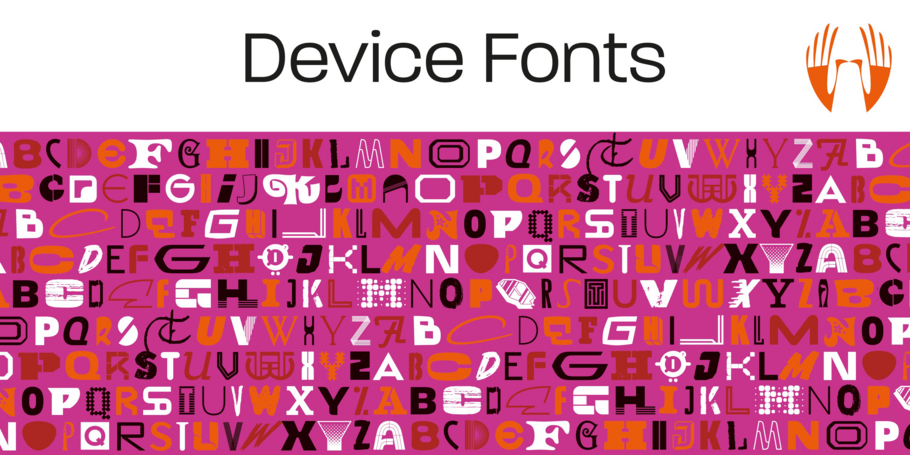
Device.
Device Fonts est la division spécialisée dans les polices de caractères du studio Device de Rian Hughes. Située à Kew Gardens, à l’ouest de Londres, elle a vu le jour en 1997 pour publier la bibliothèque de polices sans cesse plus étendue de Rian Hughes. La fonderie a créé plus de 200 polices originales couvrant plus de 1 000 graisses différentes, notamment des designs personnalisés pour des clients aussi diversifiés que les magazines Mac User (informatique) et 2000 AD (BD de science-fiction) ou Les Tortues Ninja. Hughes s’appuie sur sa carrière de dessinateur de BD et sur son métier de designer, illustrateur et lettreur pour créer une large palette de styles de polices.
Register
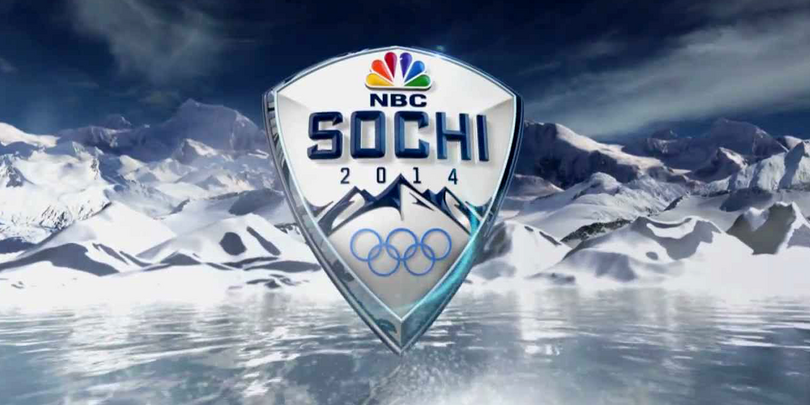
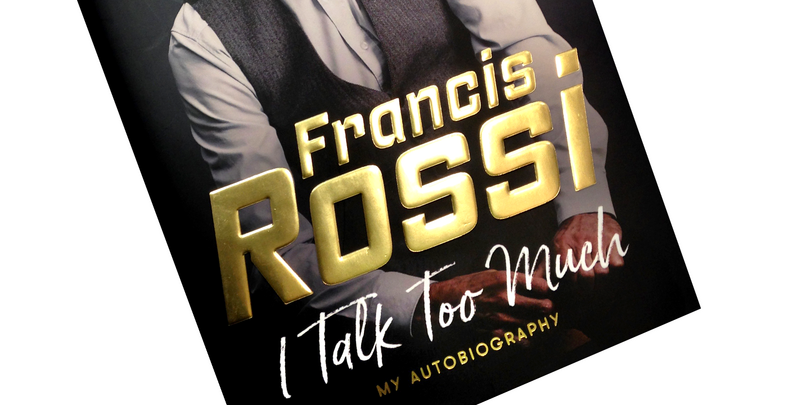
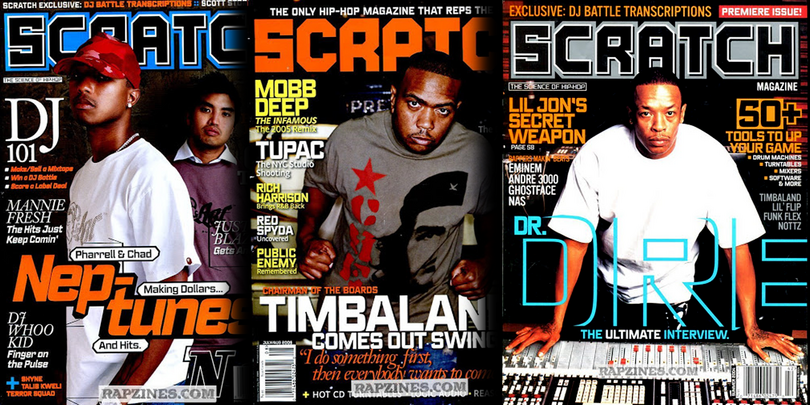
Les capitales de la police Register sont construites sur le même modèle que celles de la police Bank Gothic 1930 créée par Morris Fuller Benton pour American Type Founders, mais les courbes larges sont ici aplanies et des pièges à encre sont ajoutés pour souligner l’esthétique industrielle. Register offre également des caractères minuscules qui font défaut dans la police Bank Gothic. Ce type est disponible en deux largeurs principales, toutes deux déclinées en cinq graisses, y compris pour les graisses italiques aux formes dérivées des lettres cursives, auxquelles s’ajoute une version grasse condensée. Register a été utilisé aux Jeux olympiques de Sochi, dans le magazine Source et sur les albums publiés par Transient Records.
Regulator Nova
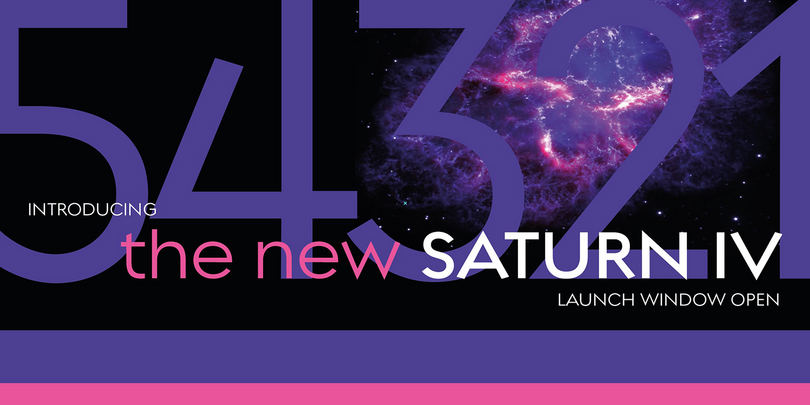
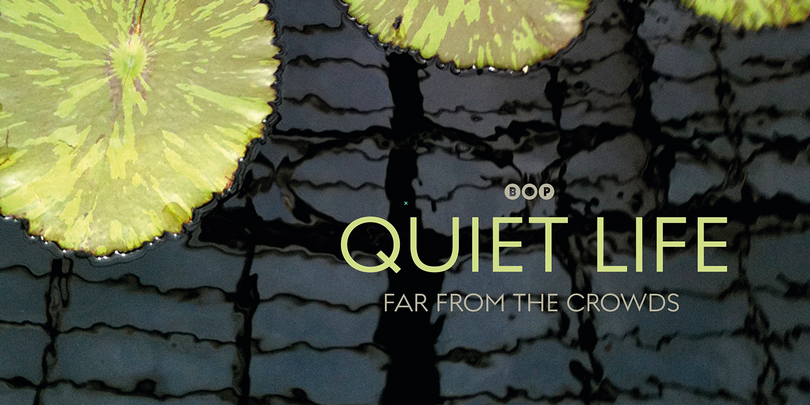
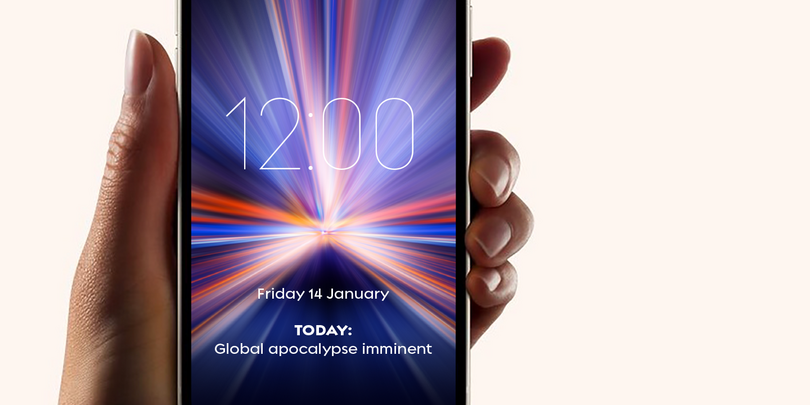
Type géométrique sans empattement se démarquant par la grande hauteur d’x des minuscules et des contreformes ouvertes, Regulator Nova est extrêmement lisible pour les corps de texte et les paramètres étendus, mais la gamme de graisses permet également de l’utiliser pour les titres. Les terminaisons des fûts présentent toutes des coupes à près de 90 degrés, ce qui confère une grande précision aux caractères. Des versions alternatives des glyphes g, j, r, w, K, R, W, # et de l’esperluette sont disponibles en graphie standard et italique, et il est possible de basculer de l’une à l’autre dans le panneau Opentype ou dans la palette de glyphes. Nette, élégante et lisible, Regulator Nova est une police aux proportions classiques basée sur un cercle et un carré circonscrits. Elle présente des similitudes structurelles avec les premiers types sans empattement comme Kabel de Rudolf Koch, mais adopte des formes plus britanniques pour les lettres « M » et « R ».
English Grotesque
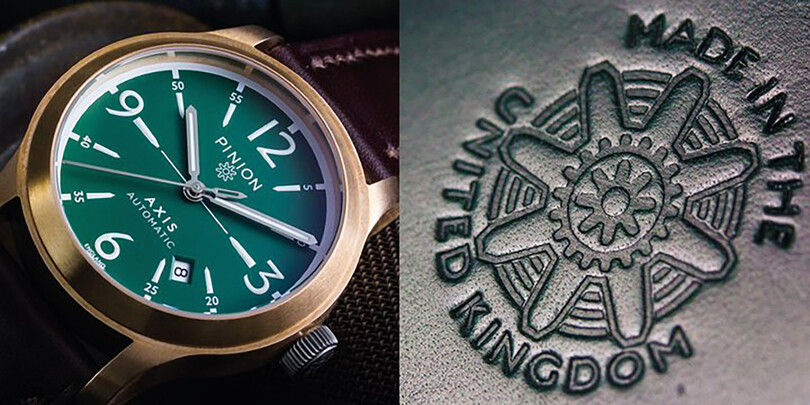
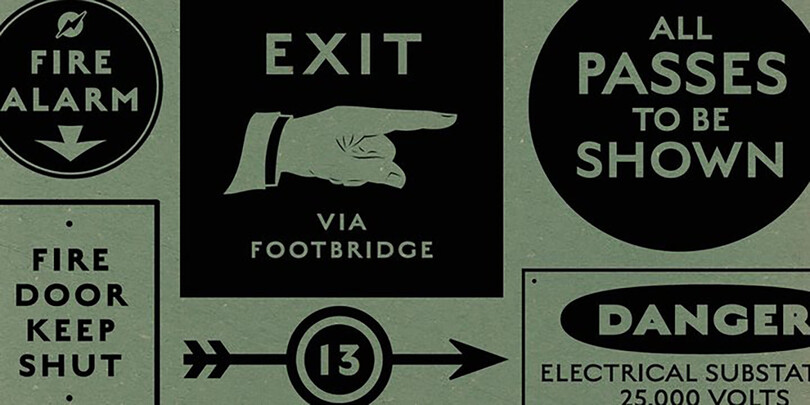
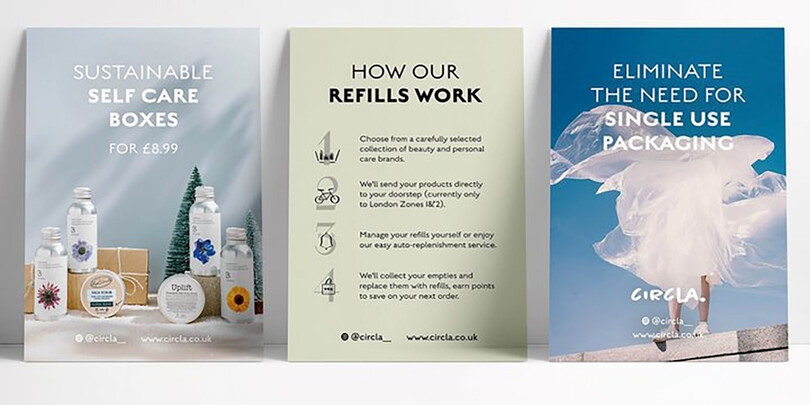
English Grotesque est un type basé sur les proportions d’un sans serif conçu au début du XXe siècle, mettant en exergue les singularités des polices de cette période. Partageant la même construction ronde et carrée des types romains Gill Sans ou Johnston Railway, ce type se caractérise par un « T » et un « W » larges, un « S » étroit et un « R » à long jambage. Du fait que l’alphabet romain ne comprenait pas de minuscules, les premiers types sans empattement empruntaient le modèle des lettres manuscrites ou cursives pour former leurs minuscules, ce qui transparaît dans la largeur plus uniforme des caractères. Par contraste, English Grotesque reprend les proportions plus distinctives des majuscules dans les minuscules. Disponible en six graisses, avec des versions alternatives en option pour les glyphes Q, &, £ et J.
Ministry
Ministry est basé sur l’alphabet utilisé à l’origine par le ministère britannique des Transports, soit un type comprenant uniquement des capitales et une seule graisse. Initialement créé dans les années 1930 pour la signalétique du réseau routier britannique, il a ensuite évolué sous l’impulsion de divers designers. Pour sa numérisation, Rian Hughes l’a étoffé d’une version bas-de-casse, d’une version italique et de plusieurs graisses. Les minuscules imitent les formes des capitales dans la mesure du possible, en s’inspirant des designers précédents pour des lettres comme le « a » et le « g », qui n’ont qu’un seul niveau en italique. Cette police britannique unique constitue désormais une famille polyvalente. Avec ses 14 graisses, Ministry convient en effet à tous les usages modernes.
Blackcurrant
Blackcurrant est l’un de ces types de Rian Hughes qui riment parfaitement avec ses dessins de silhouettes au style coloré. Inutile toutefois de représenter ses œuvres d’illustration pour saisir l’atmosphère des BD vintage: cette famille de polices y parvient sans peine. Fantasques et joyeuses, les formes asymétriques de Blackcurrant ajoutent une touche d’espièglerie aux dépliants, emballages et brochures touristiques. « Squash » est la version plus condensée et « Black » la version large de ce type. Quant à « Cameo », il arbore un look complètement unique.
Paralucent
Paralucent, un type sans serif moderne et polyvalent, est l’interprétation du modèle Helvetica/Akzidenz par le designer, qui s’est inspiré des polices industrielles de la fin du XIXe siècle, mais en a conçu une version beaucoup plus personnelle et vivante. Les graisses de texte, ajustées pour les caractères de petite taille, présentent des formes plus ouvertes ainsi qu’un interlettrage plus souple destiné à faciliter la lecture. Ce type comprend également des chiffres alignés pour les listes et les tableaux. Le design souligne l’espace négatif entre les caractères et une hauteur d’x singulièrement grande des minuscules, qui leur confère une certaine originalité et améliore la lisibilité. Cette police populaire est abondamment exploitée dans des magazines tels que Loaded, Heat et TV Quick, mais aussi dans les beaux livres de photographie grand format et sur les sites web de galeries d’art.
Urbane
Urbane est une famille sans empattement déclinée en six graisses et italiques, qui se prête à tous types d’usage. Elle explore la même notion d’espace que les premières familles géométriques sans serif inspirées de la typographie moderniste telles que Futura, Erbar, Spartan et Elegant Sans, avec notamment un « a » à un niveau, une grande hauteur d’x ajoutant une touche contemporaine et des panses très légèrement condensées. Parfaite aussi bien pour les titres que pour le corps de texte, cette police peut faire office de référence par son côté classique et bien lisible. La largeur des lettres est visuellement équilibrée, détail inhabituel chez un type sans serif géométrique moderne, ce qui lui confère un rendu harmonieux. Cette famille de polices inclut un ensemble de caractères international complet ainsi que des chiffres alignés, tabulaires et elzéviriens.
Kallisto
Police sans empattement robuste et rectangulaire aux angles et terminaisons de fûts subtilement arrondis, Kallisto allie une esthétique rationnelle et industrielle à une certaine chaleur qui émane des formes de lettres familières que l’on trouve sur les panneaux signalétiques standard estampés ou embossés. Kallisto est disponible en 10 graisses différentes et figure parmi les polices les plus vendues de Device sur MyFonts. Le designer a également créé une variante intéressante à lignes, Kallisto Lined, qui évoque les lignes de balayage, la vitesse et les écrans d’affichage.
Korolev
Korolev est une famille de polices géométrique sans serif déclinée en 72 graisses, basée sur le lettrage réalisé par un designer graphique soviétique anonyme pour les affiches de propagande déployées en 1937 durant la parade militaire sur la Place Rouge. Elle a été baptisée en hommage à Sergey Pavlovich Korolyov, ou Korolev, considéré par beaucoup comme le père du programme spatial soviétique. Rationnelle et robuste, elle est également élégante et raffinée. La superfamille Korolev comprend des versions standard, italique, condensée et ultra-condensée, chacune disponible en cinq graisses. Elle est complétée par les familles affiliées « Rounded » et « Rough ».